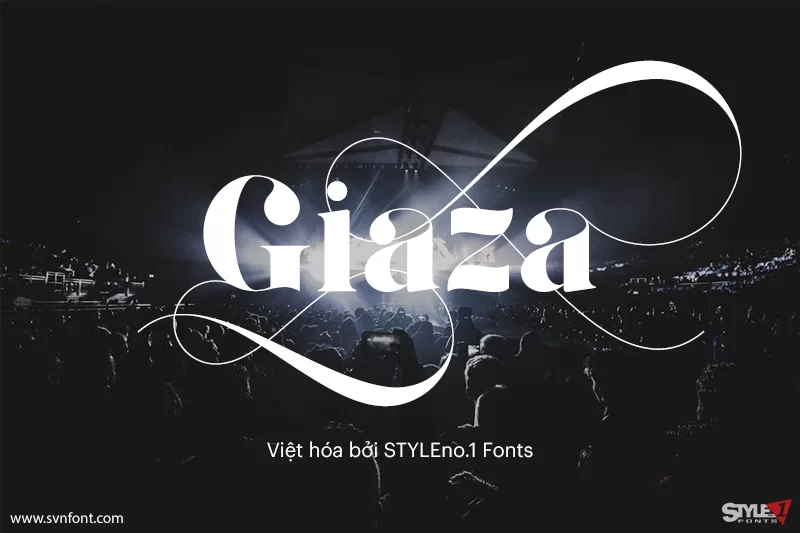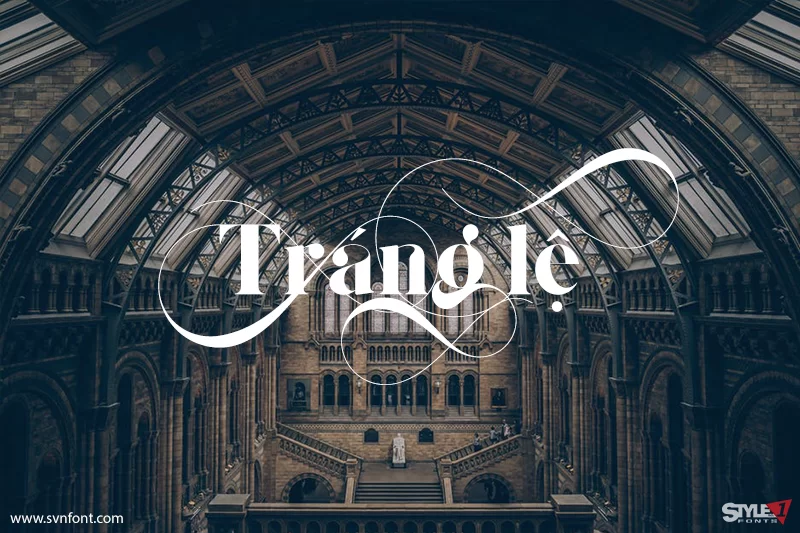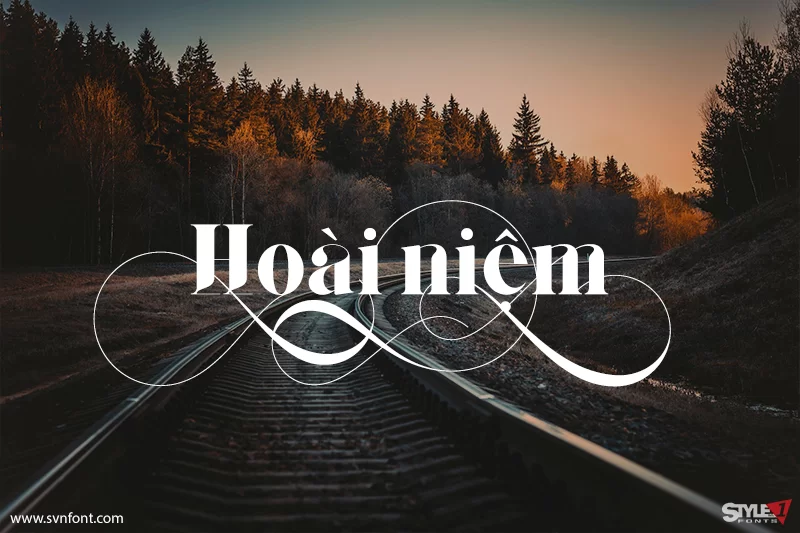
Giaza Pro là một kiểu chữ đa ngôn ngữ phù hợp với nhiều mục đích, Đám cưới, Nhà hàng, Biên tập, v.v. Phù hợp nhất với phông chữ hiển thị, trọng tâm chính là bao gồm nhiều khía cạnh thú vị nhất có thể, với 190 swashes, không ảnh hưởng đến mức độ dễ đọc.
Nhà thiết kế: AnthonyJJames
Nhà phát hành: AnthonyJJames
Việt hóa: STYLEno.1 Fonts